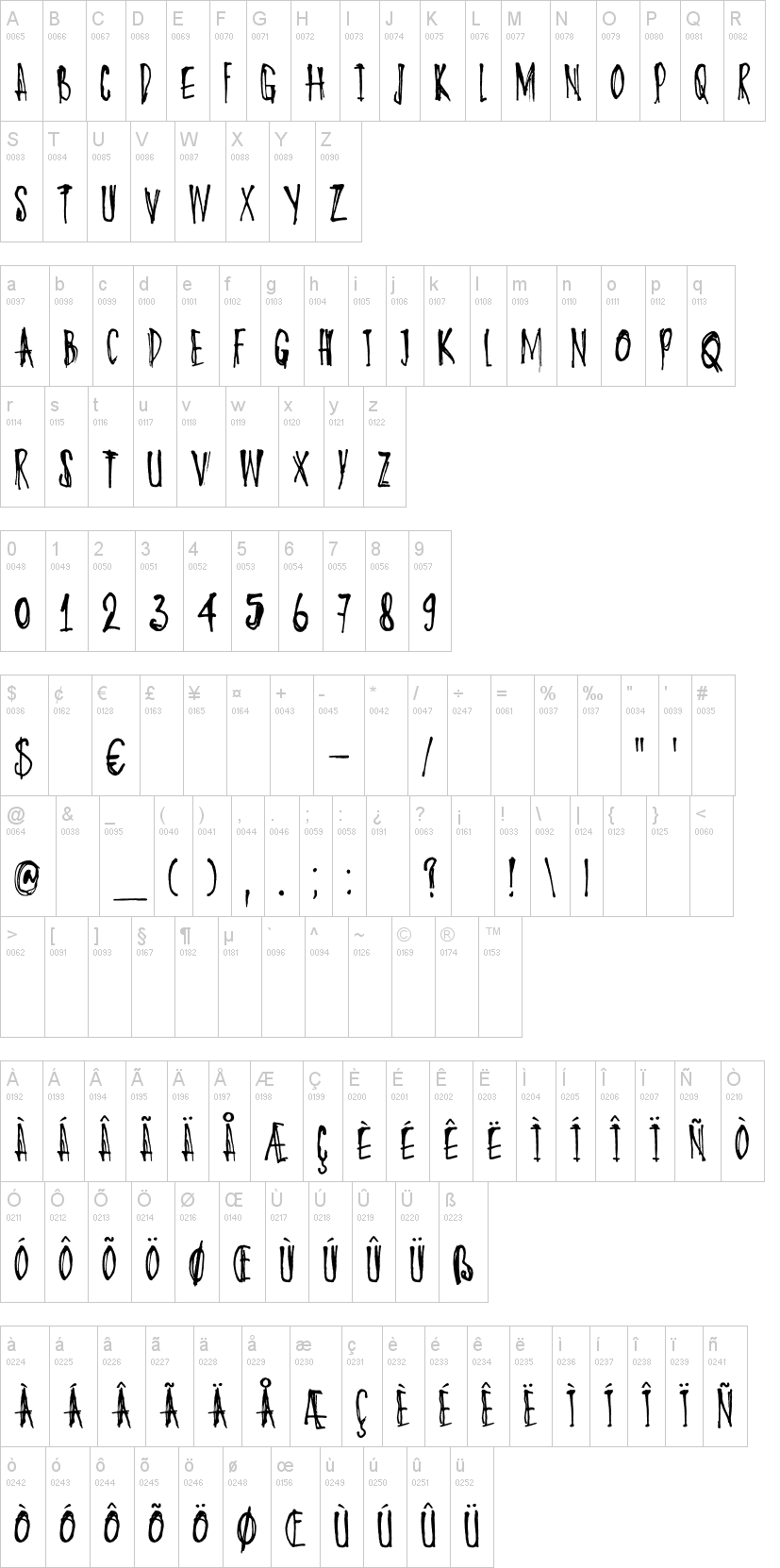
DK Oyuki's Ghost
DK Oyuki's Ghost是一款由Design Kompany创作的日本风格的字体,它有着清新的外观,丰富的细节,以及古朴的设计。字体的每一个字母都有自己独特的故事,每一个字母都有着不同的细节,以及不同的风格,给人以深刻的印象。它是一款非常优秀的日式字体,能够满足不同的设计需求。
DK Oyuki's Ghost是一款非常不错的手写艺术字体,具有很好的视觉感,适合于文化类的宣传设计、商业类品牌的广告和产品包装设计以及个性化文字排版等较多场景。